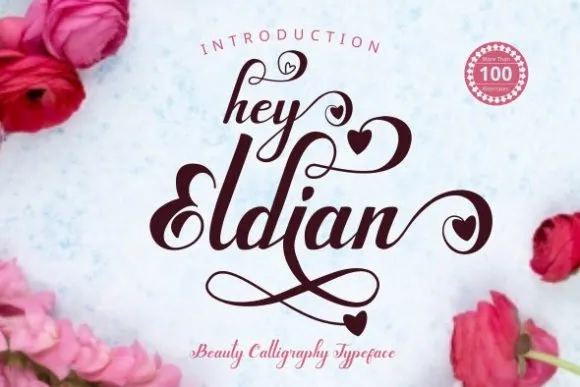
Hey Eldian Font – Fonte Grátis
Hey Eldian Font
Esta fonte foi criada a partir de escrita a mão e tem formas únicas e modernas de caligrafia. Seu estilo de escrita é muito natural. Ela foi projetada pelo estúdio Rissyletter Studio, que preserva os elementos classicamente caligráficos enquanto mantém um toque contemporâneo e fresco. Essa fonte invita você a se apaixonar por ela e transformá-la em seus projetos de forma impressionante! Ela é perfeita para designers gráficos buscam uma mistura única de modernidade e elegância clássica.